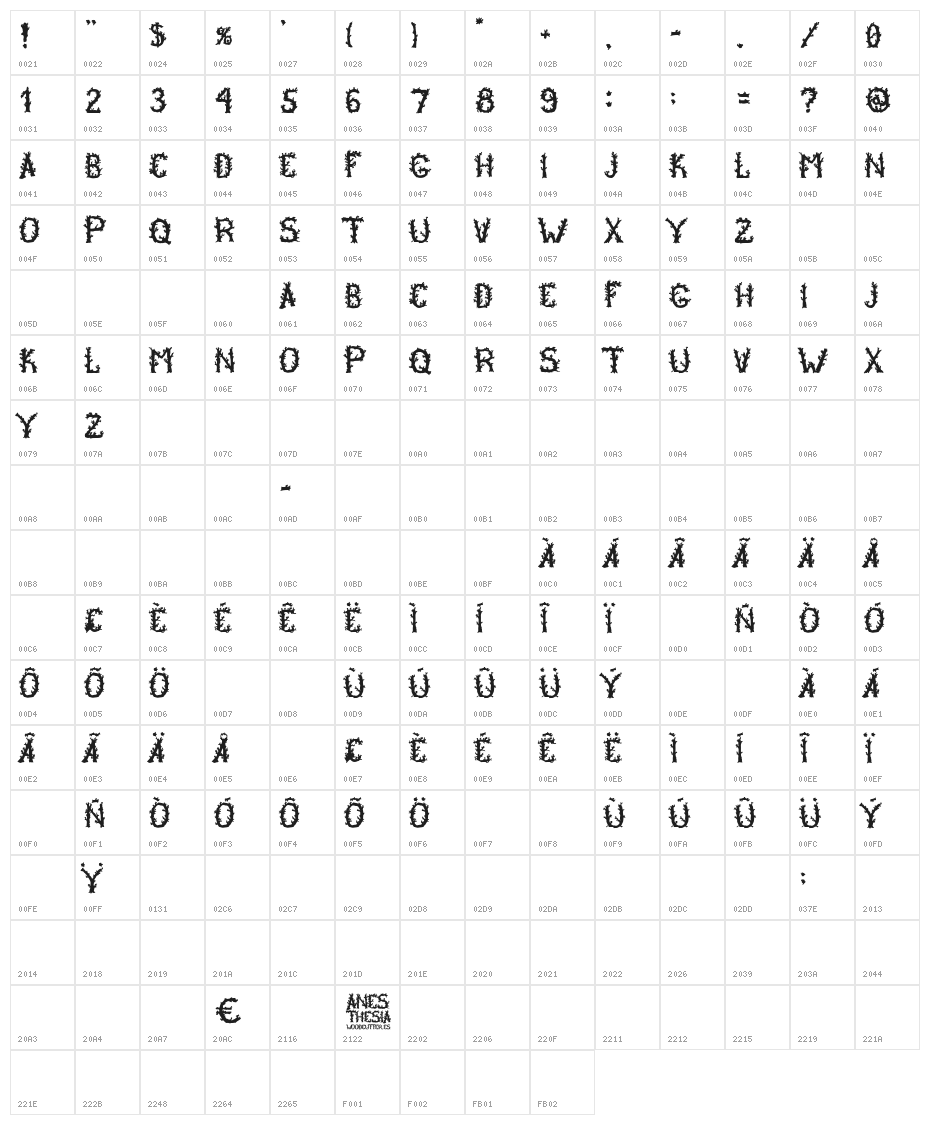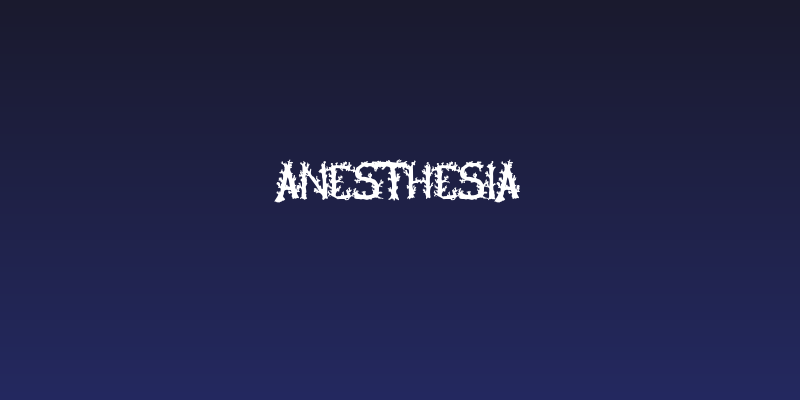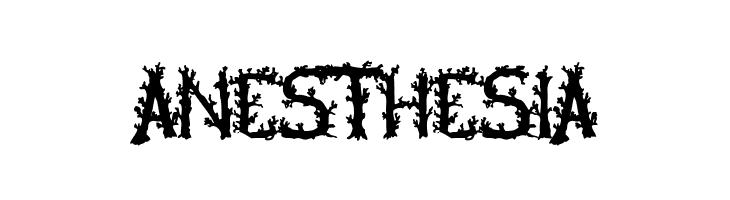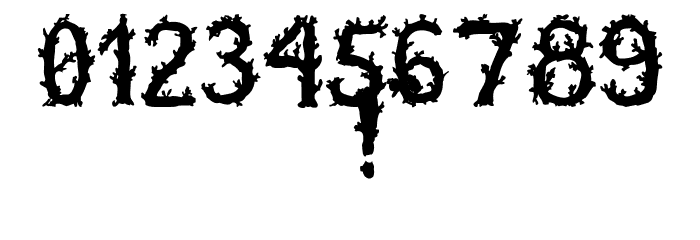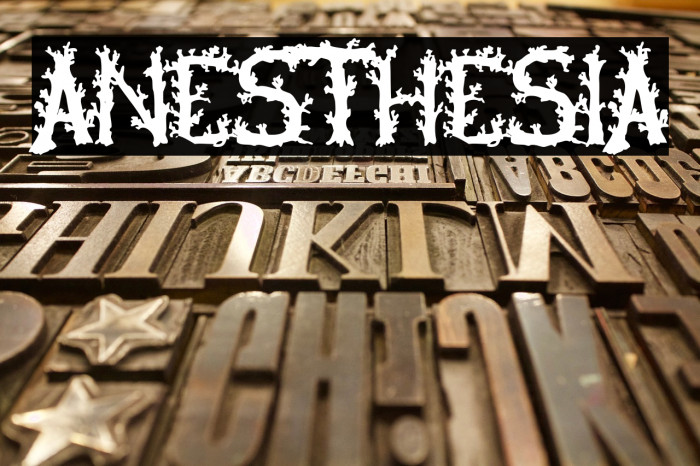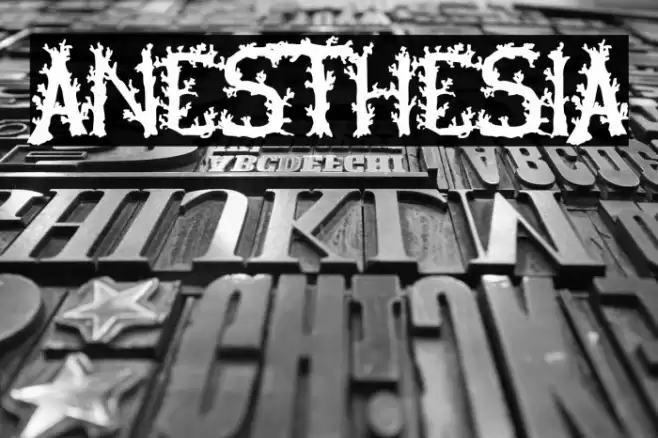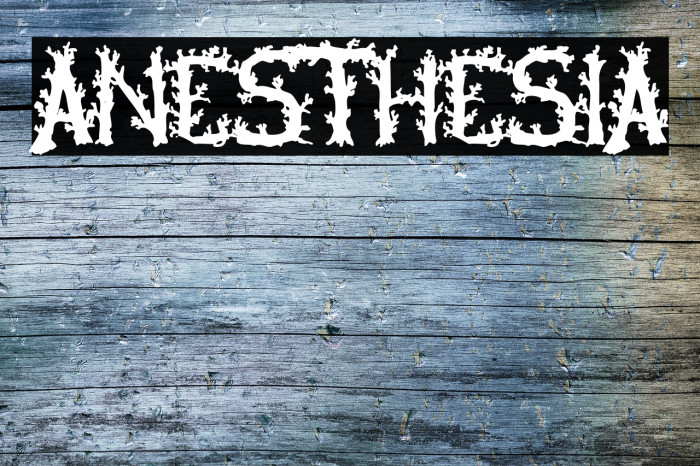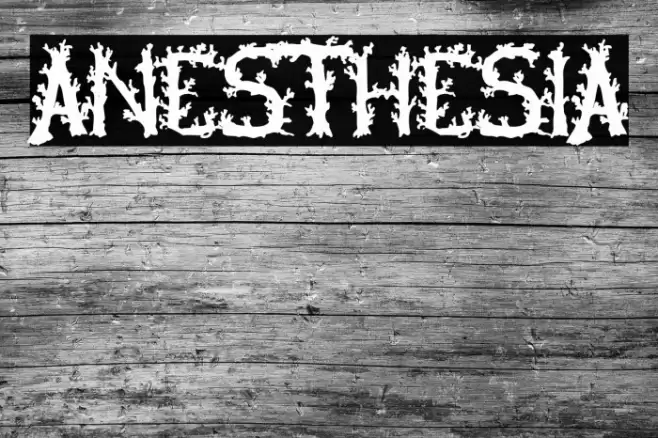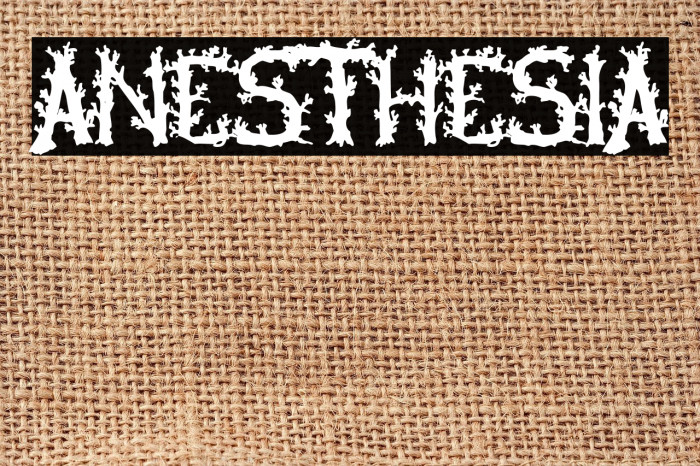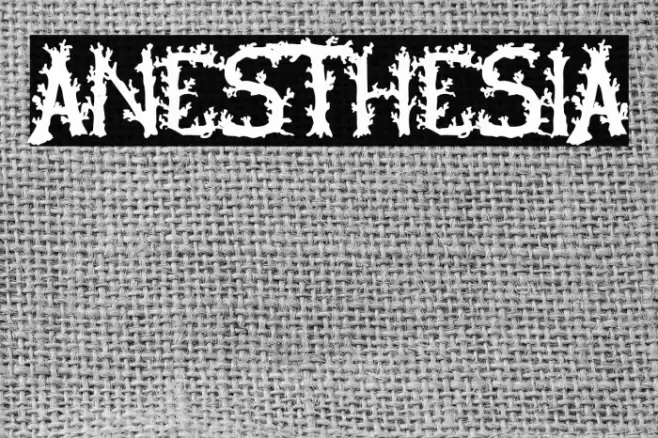
Anesthesia Font
| Proiecte propuse | Ideal for horror-themed posters, Halloween invitations, edgy album covers, or any project needing a dramatic and unique typeface. |